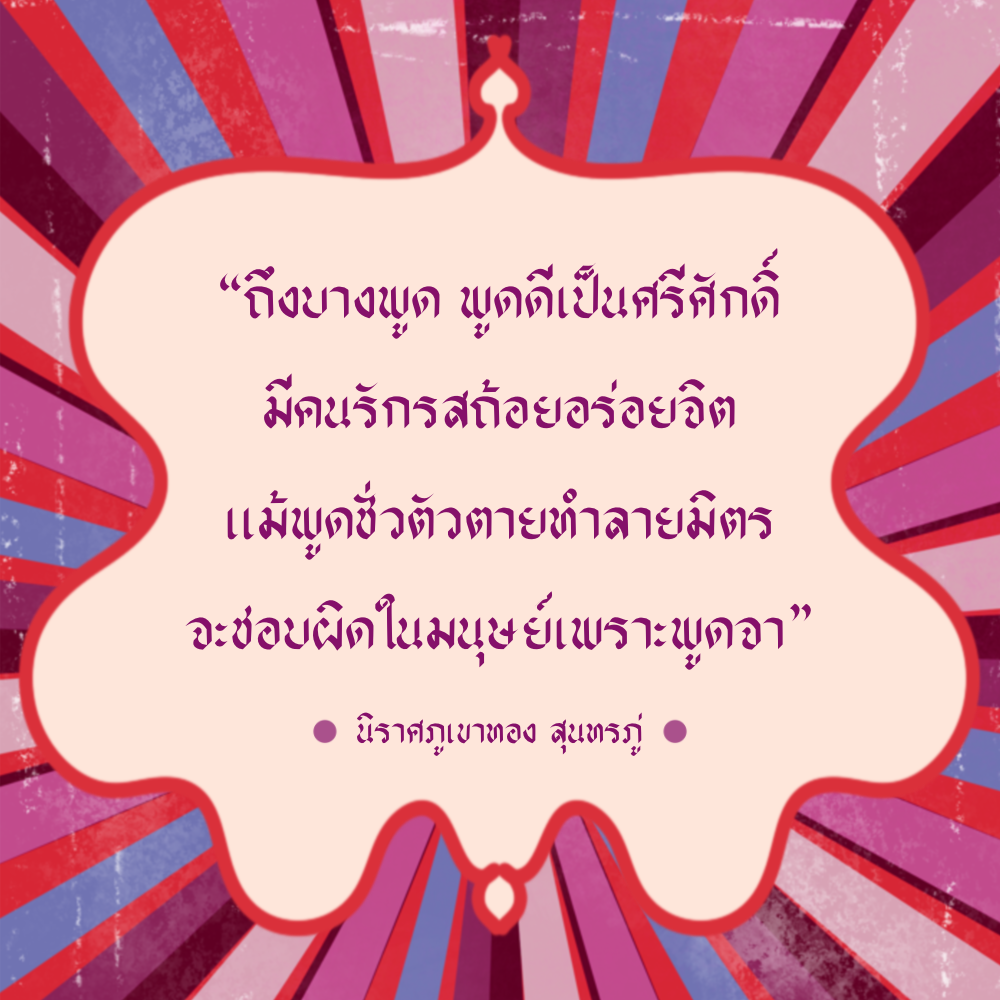
ทอศิลป์ จงเจริญ (Torsilp ChongCharoen)
ฟอนต์ ทอศิลป์ จงเจริญ
เป็นฟอนต์แบบตัวปากกาสปีดบอล
แต่พิเศษสักหน่อยคือ ชนิดตัวอักษรไม่ค่อย
ซำ้กัน บางอันเหมือนเก่า บางอันก็แปลกไป
อยากให้ได้อารมณ์คนฝึกเขียนปากกาชนิดนี้
ประเภทเดี๋ยวสวย เดี๋ยวไม่สวย ดูแล้วเป็น
คนเพิ่งฝึกเขียนดี